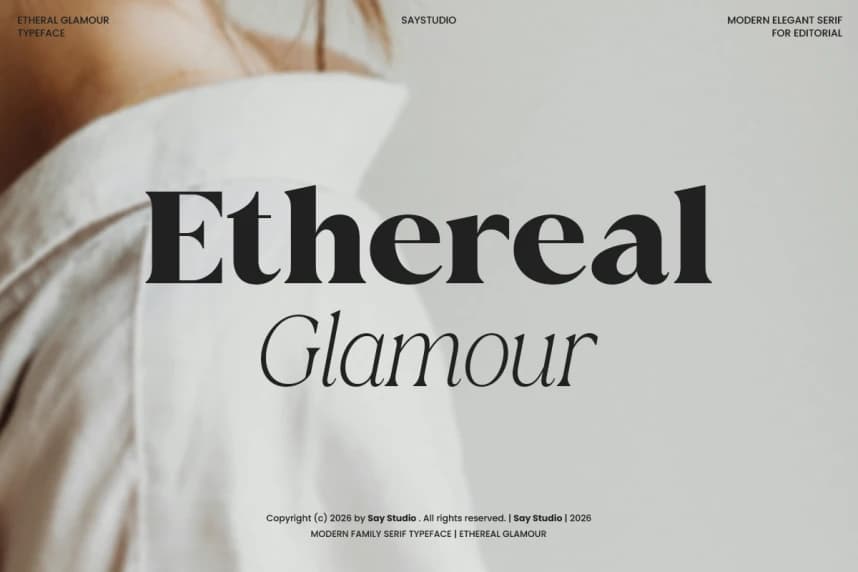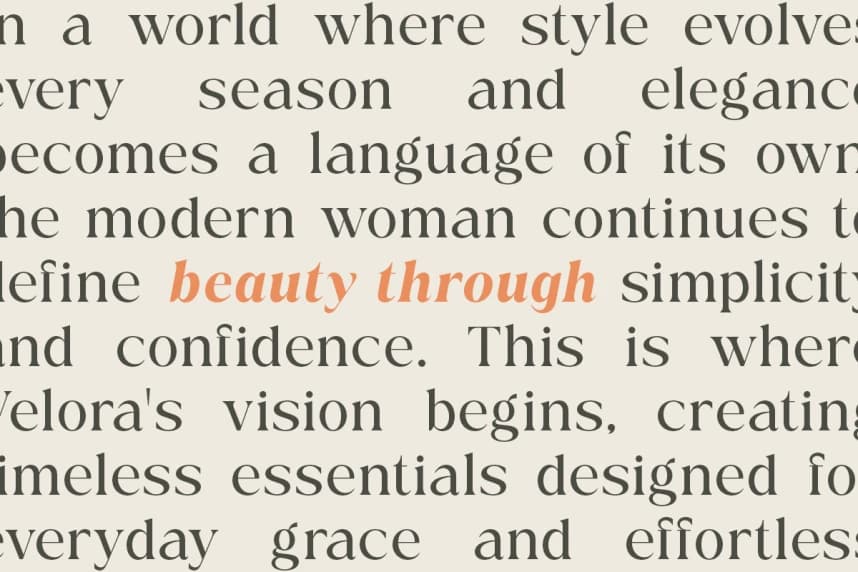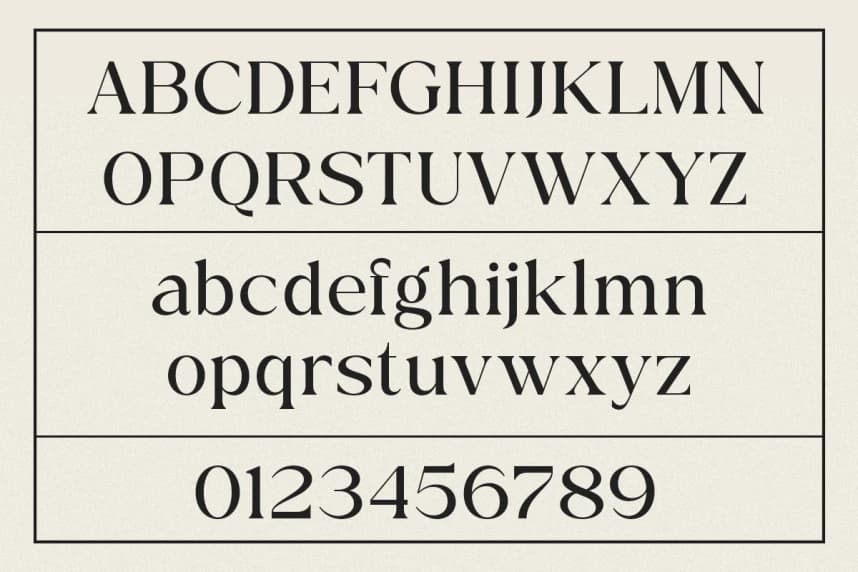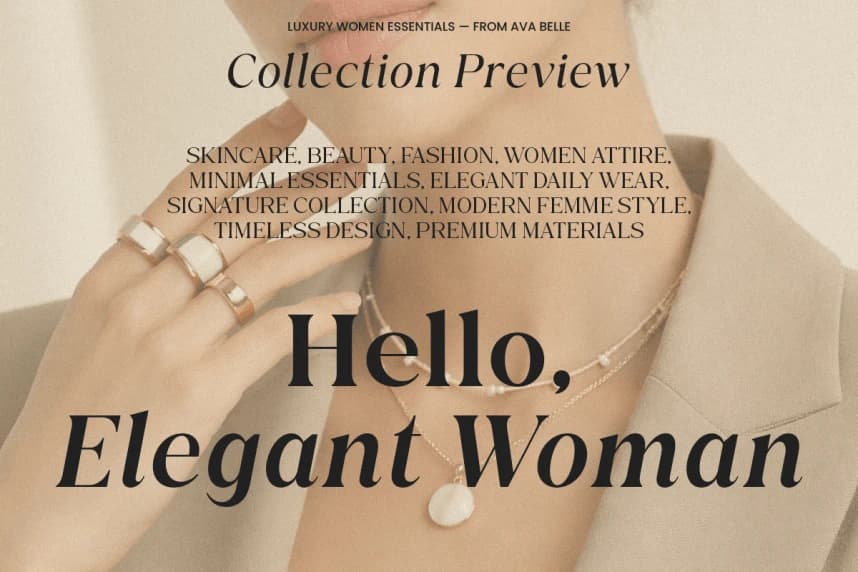
Ethereal Glamour Font
Ethereal Glamour Font, yumuşaklığı, zarafeti ve zamansız güzelliği somutlaştıran rafine bir serif yazı tipidir. Moda editoryallerinden ve zarif estetiklerden ilham alan bu yazı tipi, ince kıvrımları güçlü serif yapılarıyla bir araya getirerek sofistike bir görsel uyum yaratır.
Ethereal Glamour Font, yumuşaklığı, zarafeti ve zamansız güzelliği barındıran rafine bir serif yazı tipidir. Üst düzey moda dergilerinden ve zarif estetiklerden ilham alan bu yazı tipi, zarif eğrileri güçlü serif yapılarıyla birleştirerek sofistike bir görsel uyum yaratır.